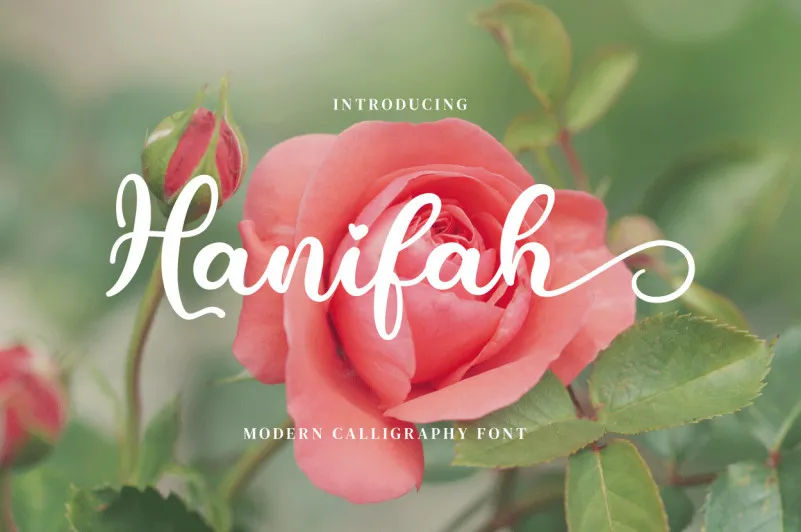
Hanifah Script Font – Fonte Grátis
Hanifah Script Font
Descubra a autêntica elegância da Hanifah Script Font, perfeita para enriquecer qualquer projeto de design com seu charme distintivo e legibilidade incrível. Com traços finos, contrastes sutilmente marcados e linhas suaves que transmitem uma atmosfera envolvente e natural, essa fonte é um verdadeiro tesouro para os amantes do desenho. Cada caractere em Hanifah Script se move de maneira sofisticada, criando texturas interessantes que ajudam a dar vida ao seu design. Para designers atentos, o Hanifah Script traz uma paleta de opções que vão desde sinos elegantes até escritas geométricas, permitindo-lhes explorar inúmeras possibilidades em qualquer projeto que estejam criando. Com esta fonte na sua caixa de ferramentas, você pode estabelecer um estilo único e expressar personalidade com a graça da calligrafia. Escolha a Hanifah Script para seu próximo projeto de design, onde sua marca irá brilhar sob uma luz mais suave. Compre agora mesmo para experimentar o fascínio desta fonte e deixe que ela transforme suas ideias em obras de arte.